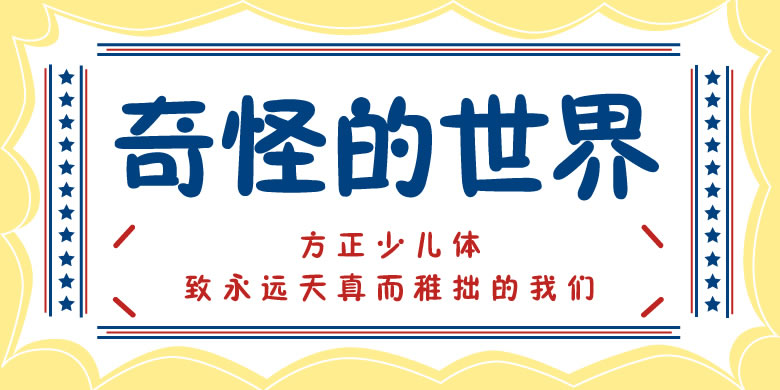
方正少儿
字体品牌: 方正字库 设计师:倪初万 字体分类:圆体、创意字体 字体属性:精品字 字符集:大陆简体(GB2312-80)、简繁扩展(GBK) 发布时间: 2000
方正少儿的设计意在模仿少儿写字的特点。这款字体的笔画圆润稚拙,字形轮廓整体统一,具有一定的易读性。方正少儿的个性纯真稚气,适用于少儿类的书刊、品牌广告和产品包装设计,以及社交网络的个性化用字,还可胜任简短的正文排版。